适合制作易拉宝的字体大全:10款实战验证的高效设计字体推荐
做易拉宝设计,字体选不对,整个画面就垮了。明明花了很多时间排版,远处一看标题模糊不清,近看又觉得不够大气。客户看了直摇头,自己也觉得不满意。
易拉宝因为是竖版长条形展示,观众通常在3-5米外观看,所以字体的选择直接决定了信息传达效果。今天我把常用的10款字体整理出来,涵盖了商业活动、企业宣传、促销打折等各类场景。掌握这些字体的使用技巧,你的易拉宝设计会少走很多弯路。
一、易拉宝大标题
思源黑体
思源黑体字体我用得最频繁。它的笔画粗壮、字形方正,3米外看标题依然清晰。我做过一次电子产品发布会的易拉宝,主标题用思源黑体Bold配上渐变色,客户当场就定稿了。
适合科技发布会、企业年会、招聘海报的主标题
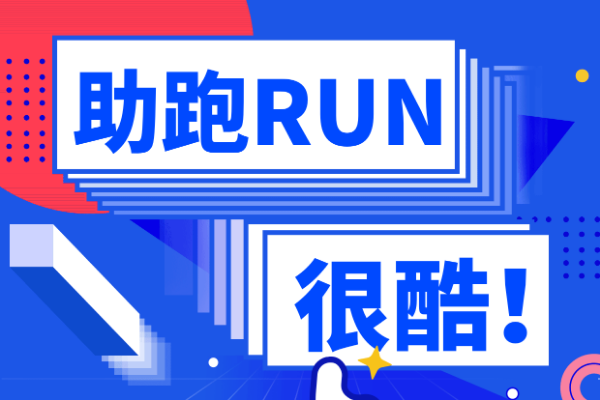
站酷酷黑
字面比普通黑体更大,笔画饱满。我有次做健身房开业易拉宝,用这个字体打出"燃脂季来袭",配上运动剪影,远远看过去就很有冲击力。唯一要注意的是,这个字体比较"重",不适合大段文字。
适用场景:运动健身、促销活动、大型展会主标题
优设标题黑
优设标题黑它的笔画经过优化,既保持了黑体的稳重,又增加了一些细节设计感。稳重中带设计感、现代商务风,适合房地产、金融理财、高端商务活动。
庞门正道标题体
笔画带点书法韵味,但比传统毛笔字更规整,拥有人文气息、有温度感。这个字体有个特点,需要字号够大才好看,建议主标题用。适合餐饮美食、文化活动、纪念庆典等场景
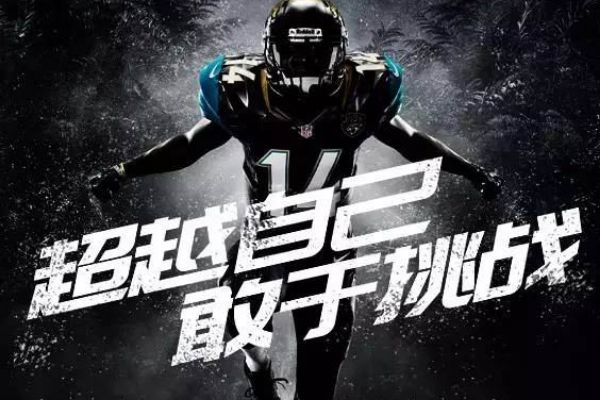
二、易拉宝副标题
思源宋体
宋体在易拉宝上其实不好用,但思源宋体是个例外。它的笔画做了现代化处理,比传统宋体更清晰。我一般用它做副标题或说明文字,搭配黑体主标题,既有层次又不抢眼。
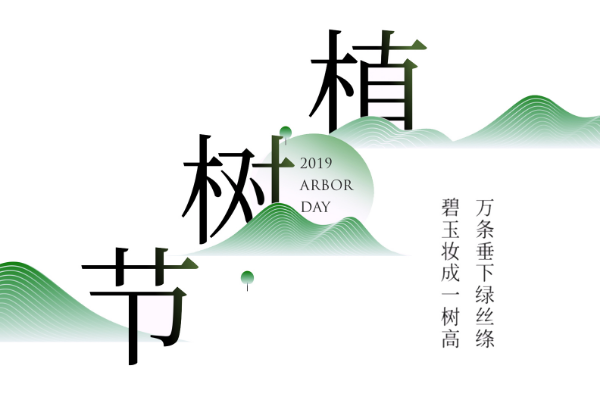
阿里巴巴普惠体
这款免费商用字体真的太实用了。笔画清晰、字形舒展,我做电商促销易拉宝时,产品说明、优惠信息都用它,密密麻麻一排文字也不会看花眼。适合电商促销、产品介绍、服务说明等中小字号文字
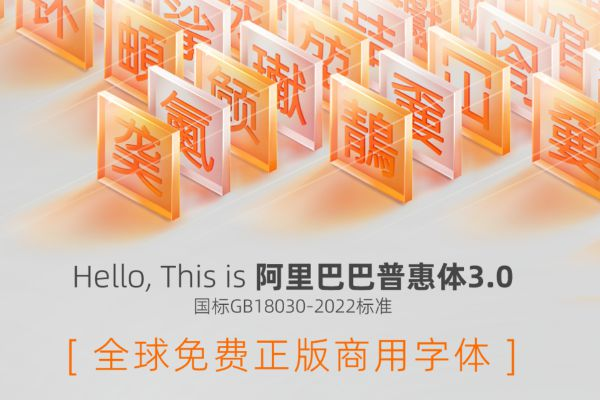
站酷快乐体
不要被名字骗了,这个字体其实很百搭。笔画圆润但不失力度,我做儿童培训机构的易拉宝时,用它来写课程介绍,家长反馈说"看着舒服,不会觉得压迫"。适用儿童教育、亲子活动、轻松主题的副标题和正文等场景。
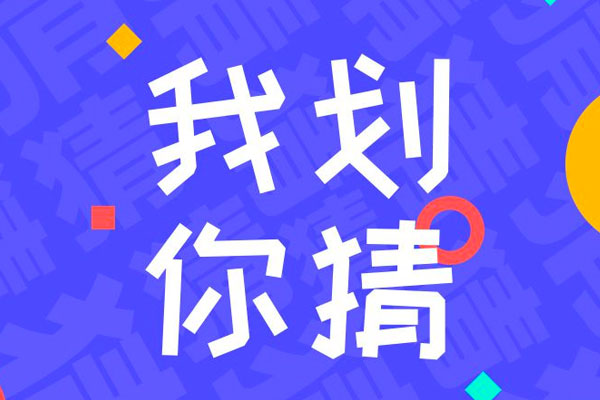
三、比较有吸引力的字体
胡晓波骚包体
笔画夸张、富有动感,我做过奶茶店开业易拉宝,标题"第二杯半价"用这个字体,路过的人回头率明显提高。不过要慎用,太正式的场合不合适。适合餐饮促销、网红店宣传、年轻化品牌活动。
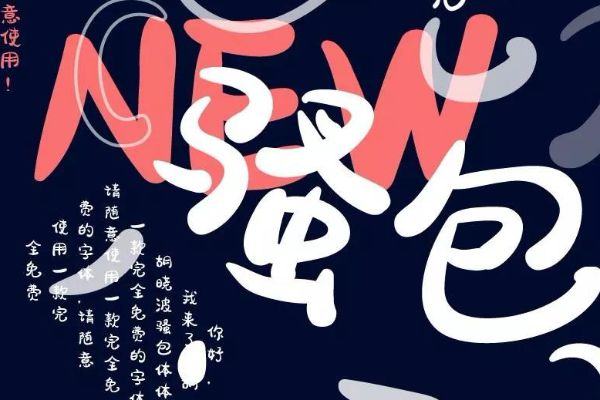
演示悠然小楷
演示悠然小楷是一款手写毛笔小楷字体,虽然叫"小楷",但放大后用在易拉宝上别有韵味。我给书法培训班做招生易拉宝时,标题"静心习字 修身养性"用这个字体,配上宣纸底纹,很多家长看了就咨询报名。适合书法培训、国学教育、传统文化推广
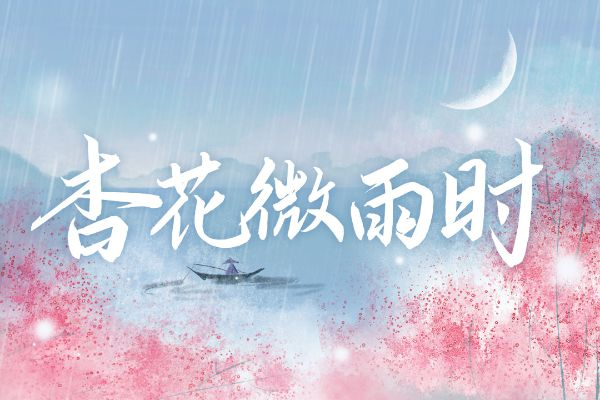
字体圈欣意冠黑体
这款字体的特点是笔画对比强烈,横细竖粗。对比强烈、现代设计感,适合时尚品牌、潮流活动、设计感强的商业宣传。
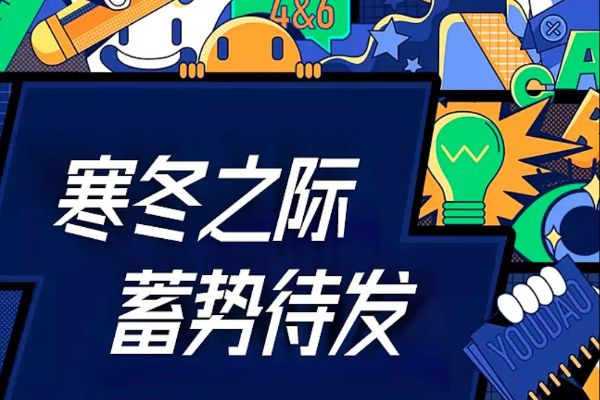
五、我的易拉宝字体匹配建议
主标题一定要粗,我一般用Bold或Heavy级别,字号至少80pt起步。副标题和正文选择Medium或Regular,字号控制在24-36pt之间。颜色对比要明显,深色背景配亮色字,浅色背景配深色字,别玩渐变色文字,远处根本看不清。
字体最多用两款,主标题一款,正文一款。用三款以上就乱了,我吃过这个亏。中文和英文可以分开选字体,比如中文用思源黑体,英文用Arial Bold,搭配起来更协调。
易拉宝不是海报,信息要精简。我现在做设计,标题不超过12个字,正文不超过50字。字太多了,观众扫一眼就走了,根本不会停下来细看。